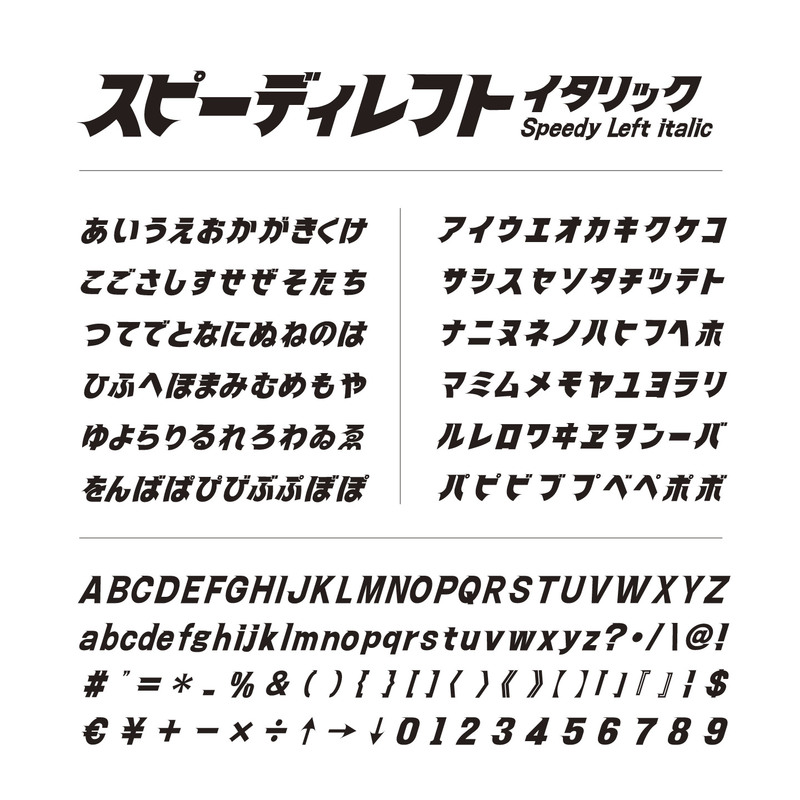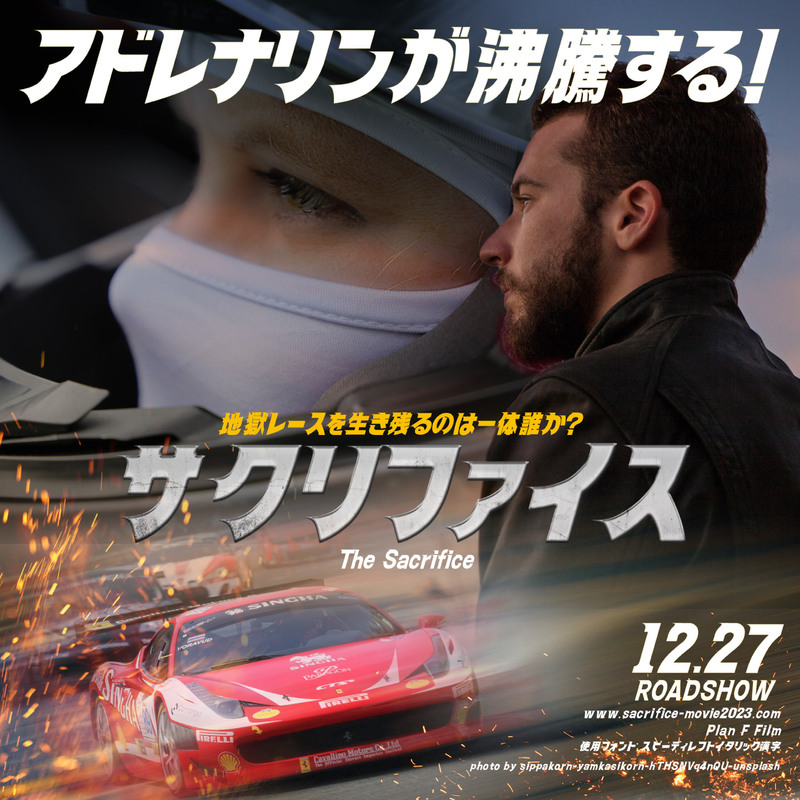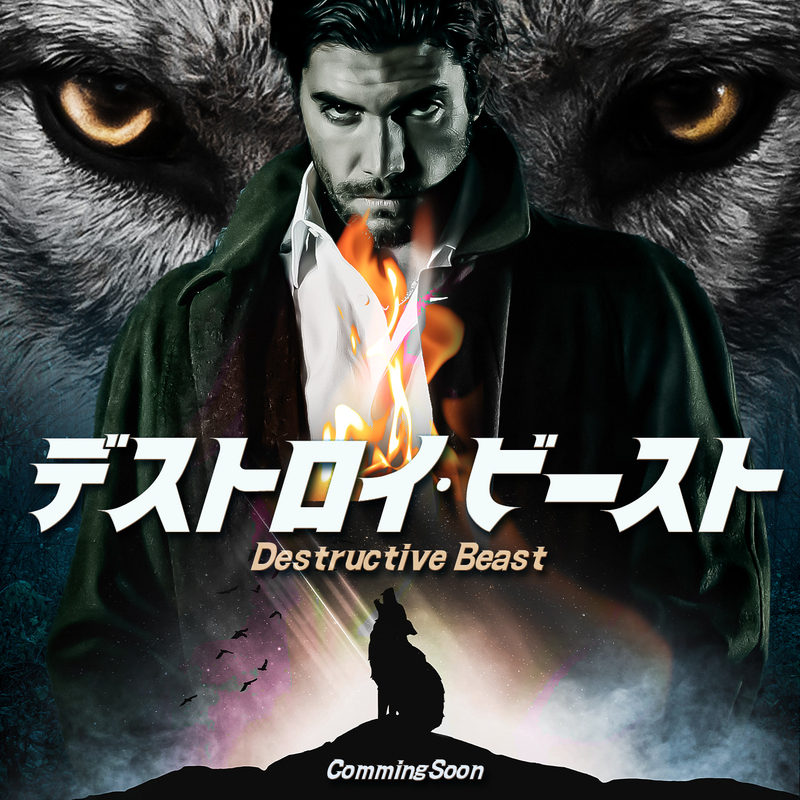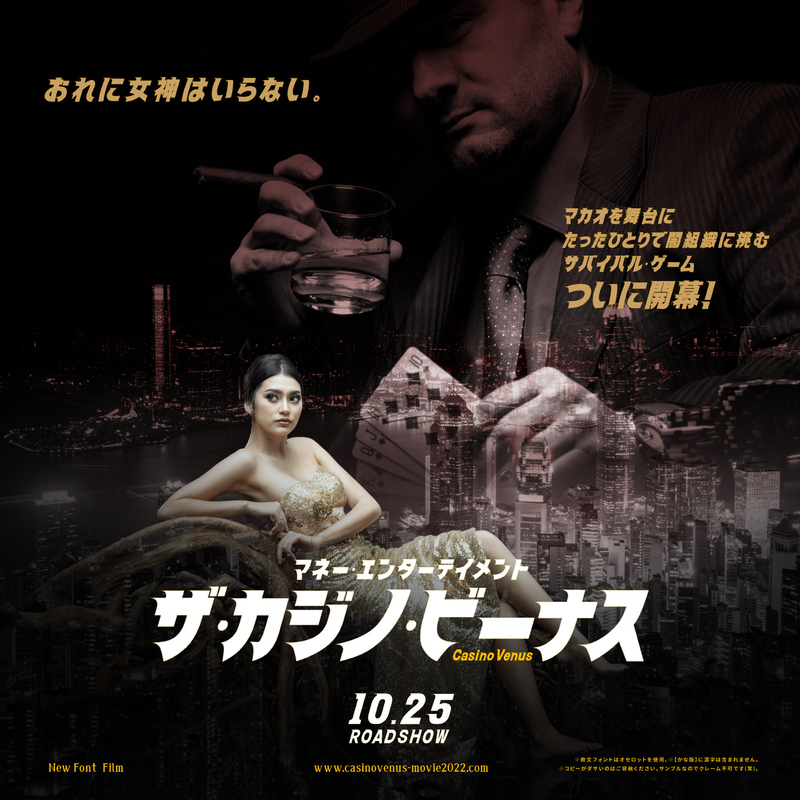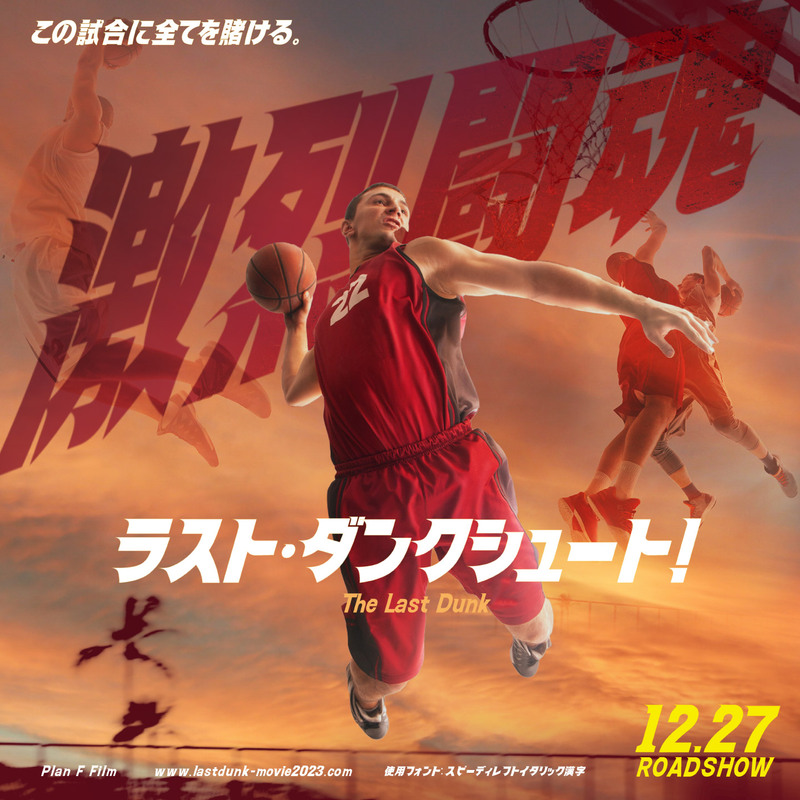
スピード感あふれるラインを表現した商用利用可能なオリジナルフォント。スピーディライトのコーナーの流れを左向き(逆向き)にしたものです。モーターサイクル、スポーツ関連ロゴの作成などに便利です。
かな、アルファベット、試用として漢字約640字(教育漢字1-4学年)を収納。アウトライン抽出可・収録文字数869字。このフォントは【かな版】【漢字版】の2タイプがございます。